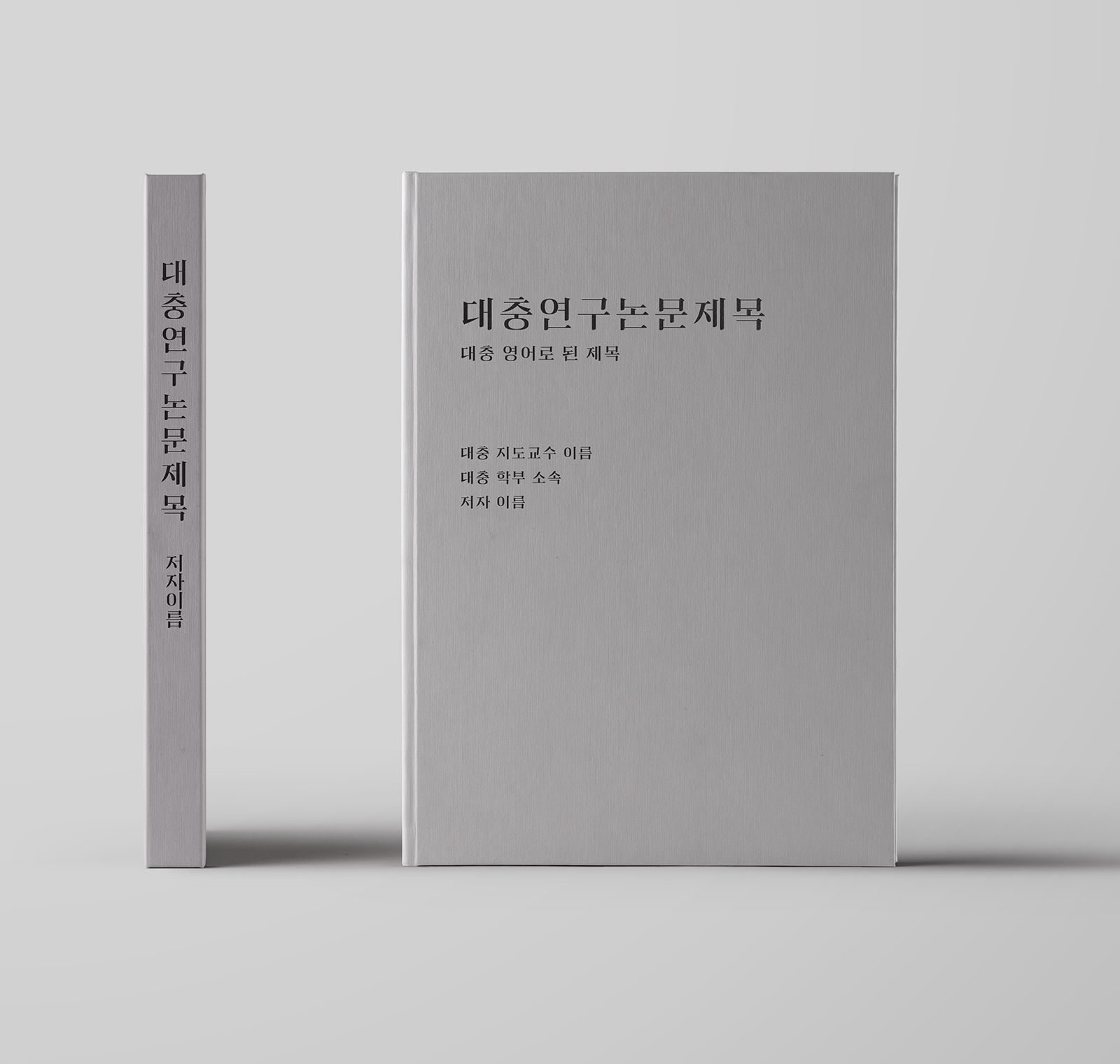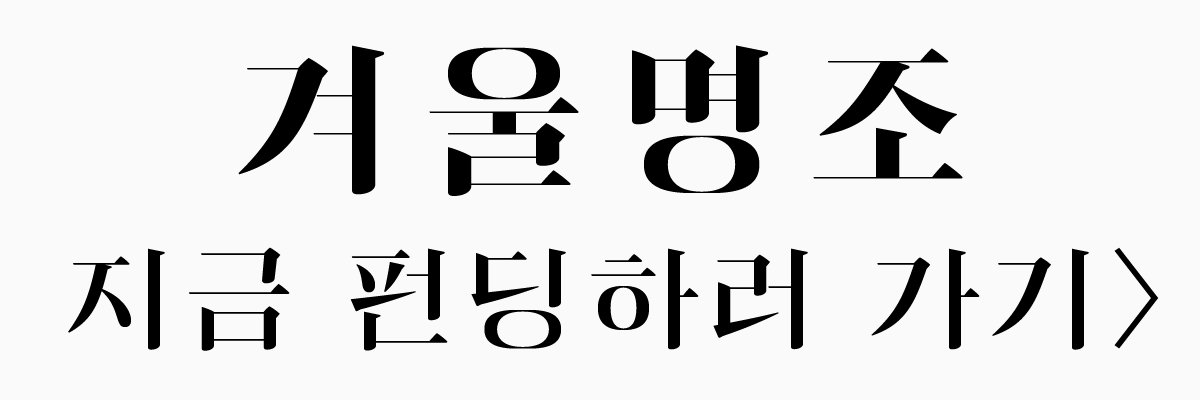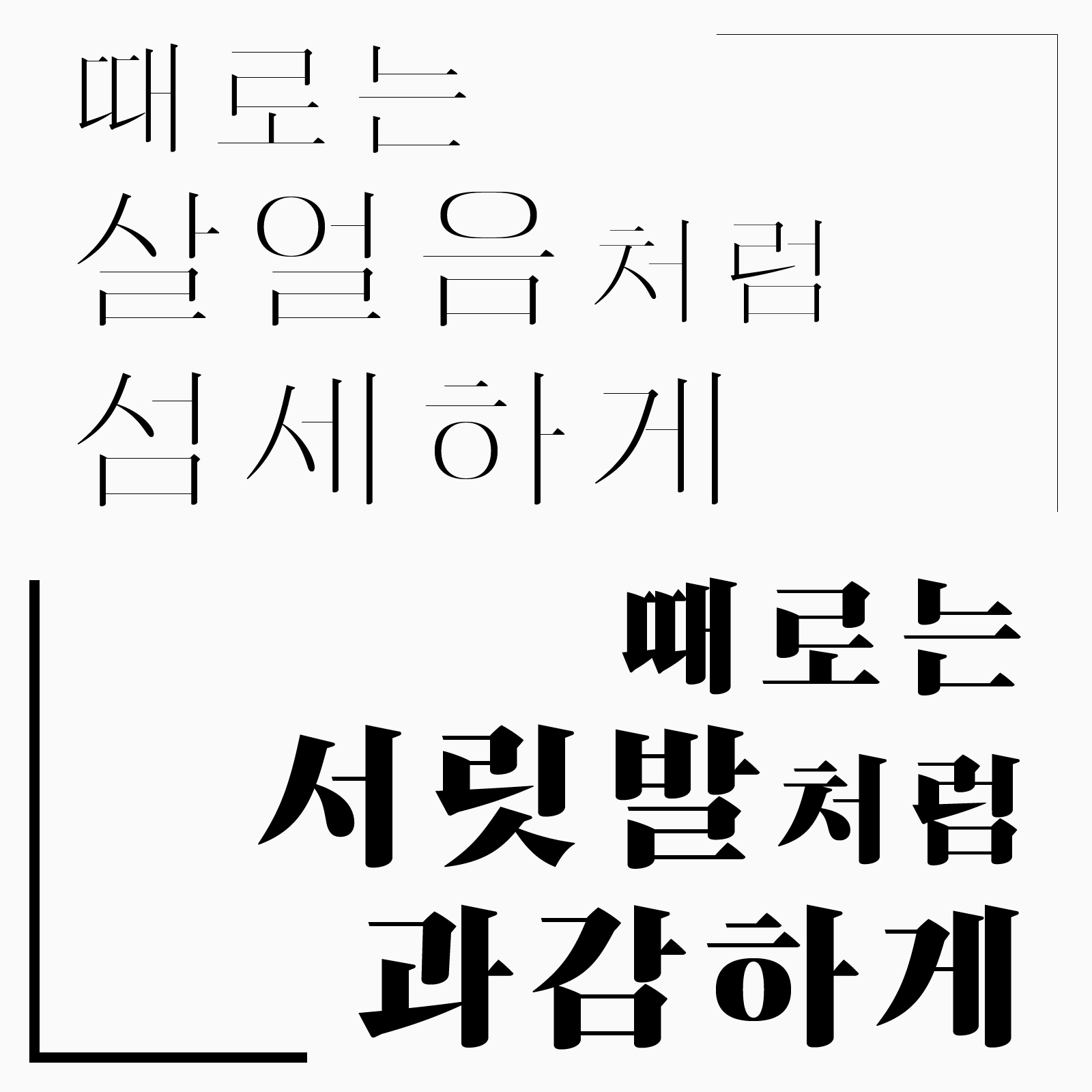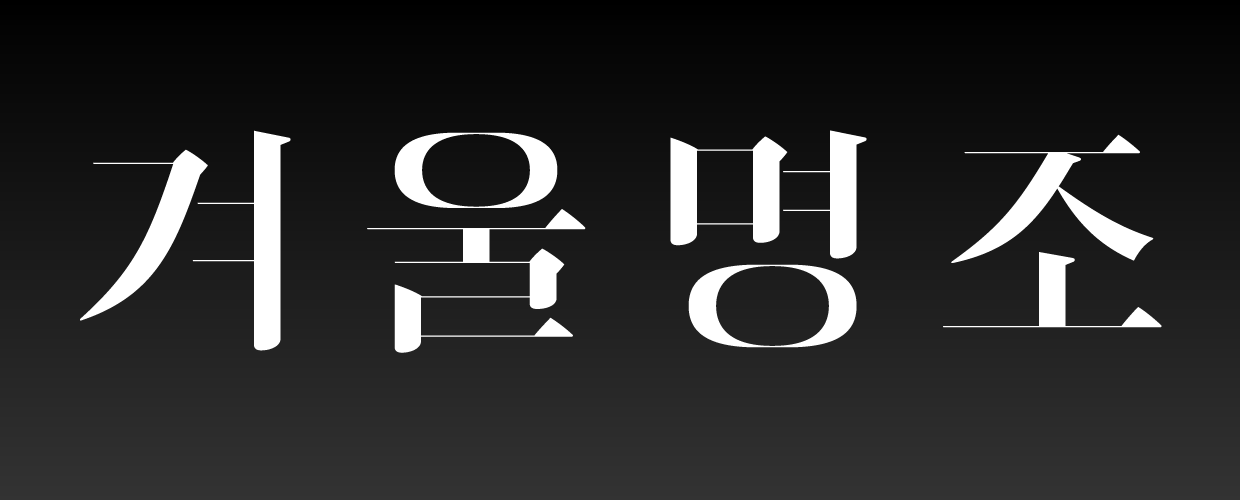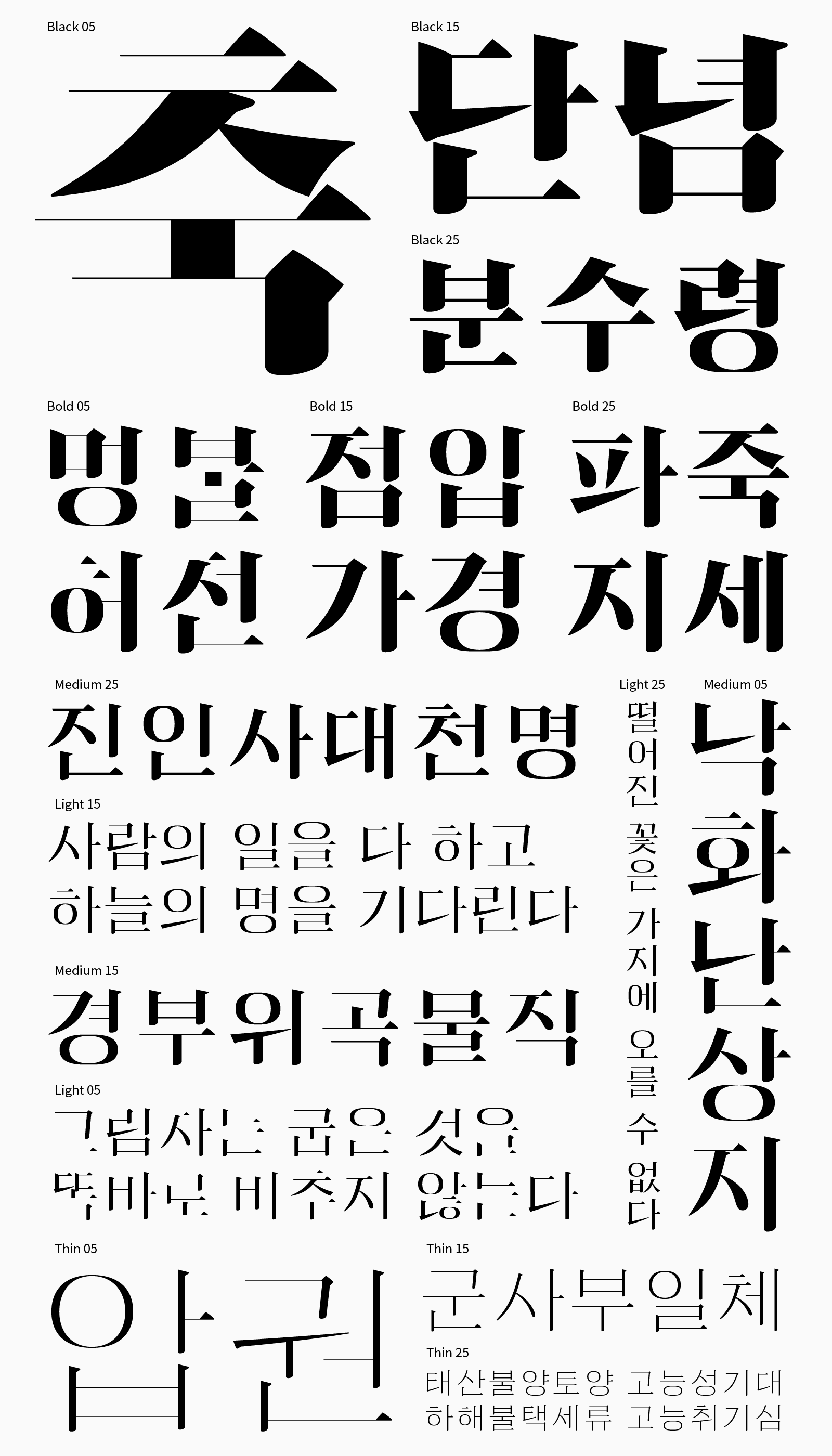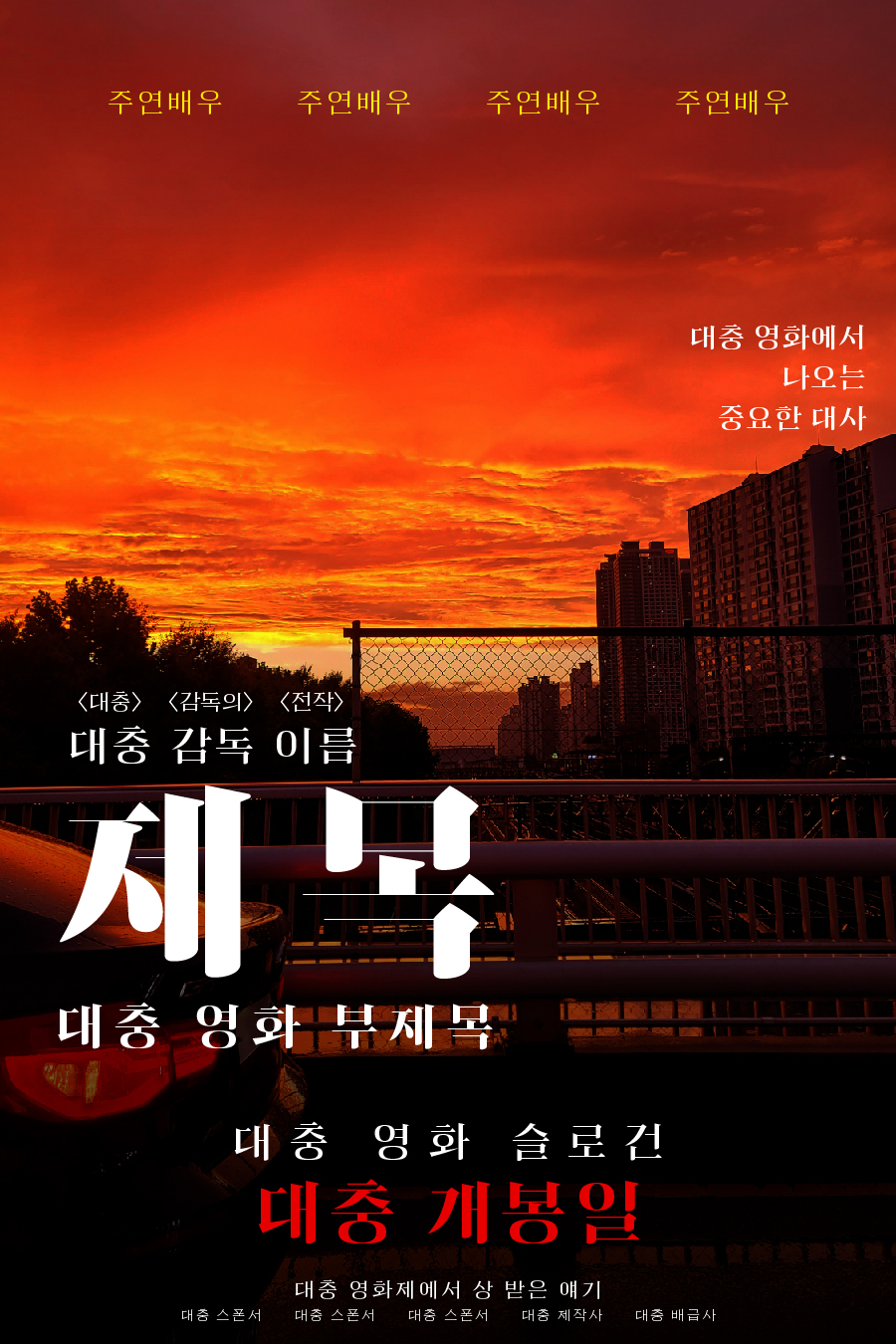
오늘은 제가 지금 제작 중인 폰트에 대해 소개해드리겠습니다.
제가 지금 제작 중인 폰트는 '겨울명조'라고 합니다.
겨울명조는 근본 명조로의 회귀를 컨셉으로, 퇴색되고 잊혀진 과거의 윤전인쇄 시대 명조를 부활시켜 지금의 디지털 시대에 맞게 새로 제작하는 것을 목표로 하고 있습니다.
우리가 평소에 부르는 '명조체'는 사실 '바탕체'입니다.
요즘의 폰트들은 명칭과는 반대로 대부분이 바탕체지요. 명조체는 보기 드뭅니다.
오히려 지금 볼 수 있는 명조들은 대부분이 레트로 스타일의 폰트들이고, 최신 트렌드를 반영하려는 시도는 보기 힘든 것이 지금입니다.
저는 명조체가 처한 이러한 현실이 너무 안타까웠습니다.
겨울명조는 이러한 계기를 시작으로 만들게 된 배리어블 디스플레이 한글명조입니다.
획의 요소요소마다 불필요한 곡선을 없애고 형태를 단순화하여 간결하고 명확하게 표현하였습니다.
가로획과 세로획의 굵기를 각각 조절할 수 있으며, 그로 인해 다양한 인상을 연출할 수 있습니다.
또한 배리어블 폰트로도 제작되어 더욱 섬세한 굵기 조절이 가능합니다.